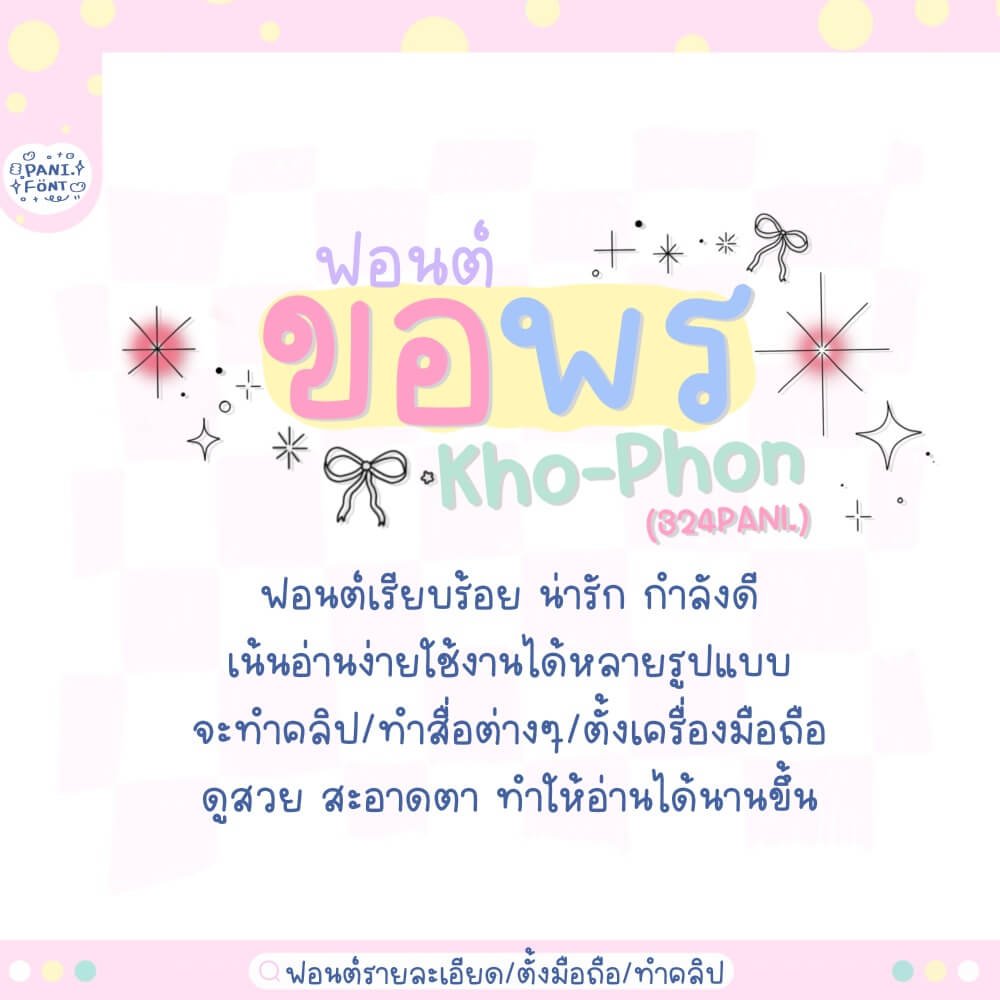
324PANI.ขอพร (324PANIKhoPhon)
ฟอนต์ 324PANI.ขอพร โหลดใช้ฟรีตัว Demo – ฟอนต์เรียบร้อย น่ารัก ทันสมัย กำลังดี เน้นอ่านง่ายใช้งานได้หลายรูปแบบ จะทำคลิป/ทำสื่อต่างๆ ดูสวย สะอาดตา สายคอนเทนต์ สายตั้งเป็นฟอนต์เครื่อง แนะนำค่ะ!!